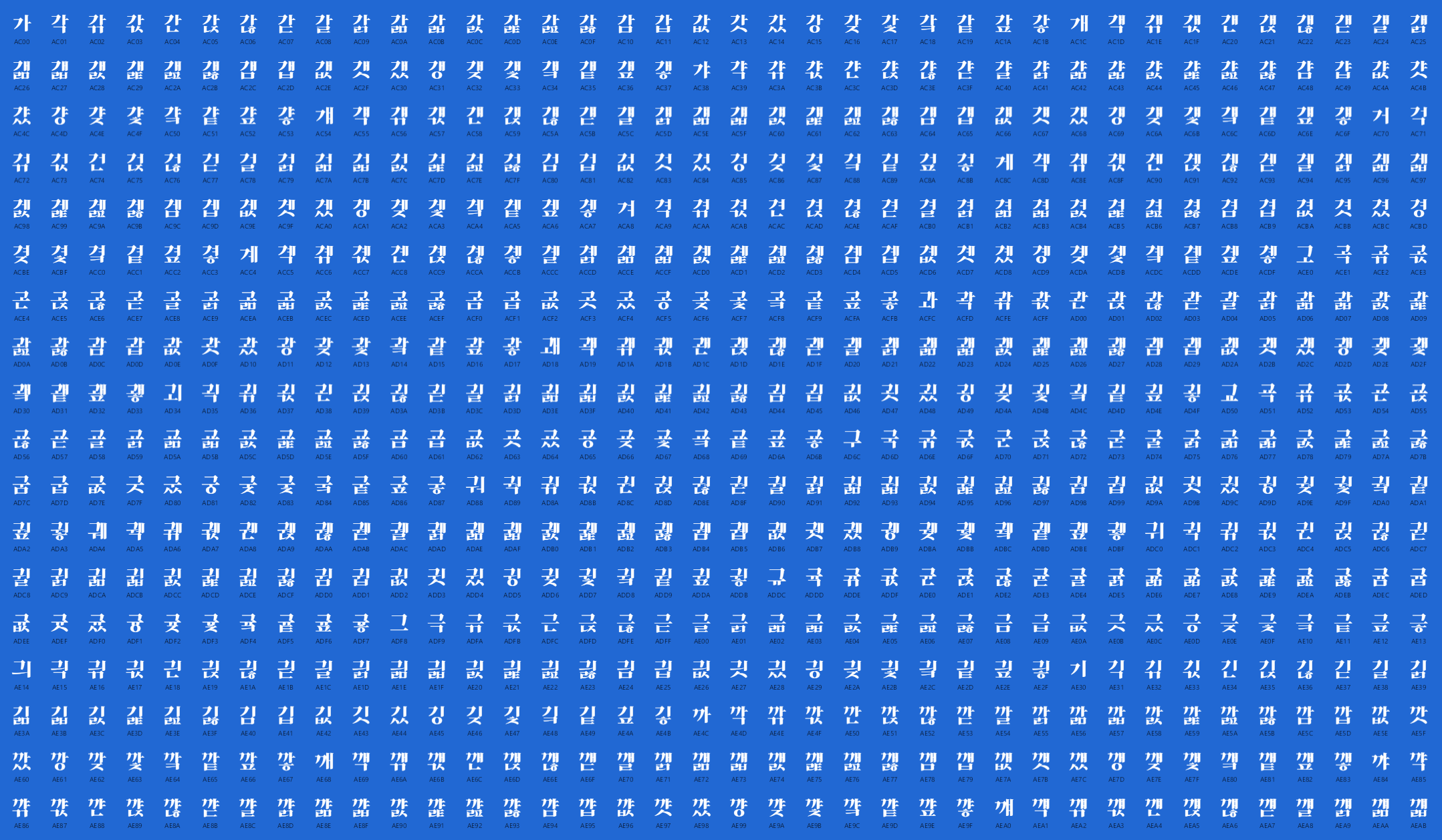
HangSong:宋体谚文 特粗
我先前专栏中谈过,思源宋配的谚文不是“宋体”的,似乎也没免费OFL的宋体谚文。今天(2025年6月7日)随便试了试,发现相比汉字做起来太容易了,这就成了字体费米悖论:既然这么容易为什么没人做,会不会已经撞车了?
结果做完统一码全部11172个谚文音节不到24小时。
当然我完全不懂谚文,在朝韩人看来可能是“老外宋”“あおさぎ\aosagi”的效果。
使用了思源的笔画,因此以OFL授权。但 谚文字母(Hangul Jamo)ᄂ\ㄴ(居左)不适用中文的竖折或竖钩,因为会遮挡其上下的字母(如:넉),为此我原创了ᄂ\ㄴ笔画。而ᄋ\ㅇ是以前原创的。
在ISO四字代码中,谚文音节|한글|Hangul Syllables 的代码是Hang,因此字体简单命名为“HangSong”(有更好的名称请留言),当前发布的字重为Heavy,相当于思源宋的最粗,也推荐搭配思源宋Heavy韩标的汉字。以后有时间或改为可变字重。
经过一番讨论,下一版本字体添加韩语名为명조언문,大意是“明朝谚文”。
下一版将修正一个“偏旁”的写法,在研究是否改为可变字体,同时搭配司源赢宋作窄体。
备考:언문(諺文)
调整全局度量,提升100单位。参考不含汉字的韩国字体,添加韩语用到的标点和几个符号,尤其是做成衬线体的~和中点\가운뎃점“ㆍ”(?)
注意到韩国字体里全角标点非全角,照搬。若还缺少什么标点请告知。
修改并补全ASCII部分(尤其是做成衬线体的<>^。思源宋里^是黑体,但Â的ˆ又是衬线体,不统一),补充若干标点,新增一大批谚文字母(比如ㅁᄆᆷᄆᆼᄋㅇᄋ,算是谚文的“偏旁”,覆盖韩国字体实际用的那部分)
顺带字体里也放了些彩蛋性质的字形,比如曲率连续的太极图☯